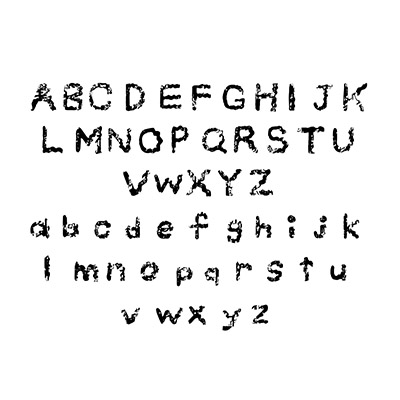
true color
ArtistTEN TONE
Designer岡崎 遥香
OrganizationTENTONE
個性豊かな施設の雰囲気が最大限伝わるフォントを作りたいと思い、渋谷フォントに関わってくれたアーティストさん全員に参加してもらって制作したフォントです。アーティストさんに描いてもらったtentoneという文字を重ねて、その上から大元の文字でくり抜いて制作しました。tentone(十人十色)という意味と掛け合わせ、このフォントを使うことで、使った人が自分自身の本当の色を発揮できるようにという思いを込めてこの名前をつけました。(岡崎 遥香)